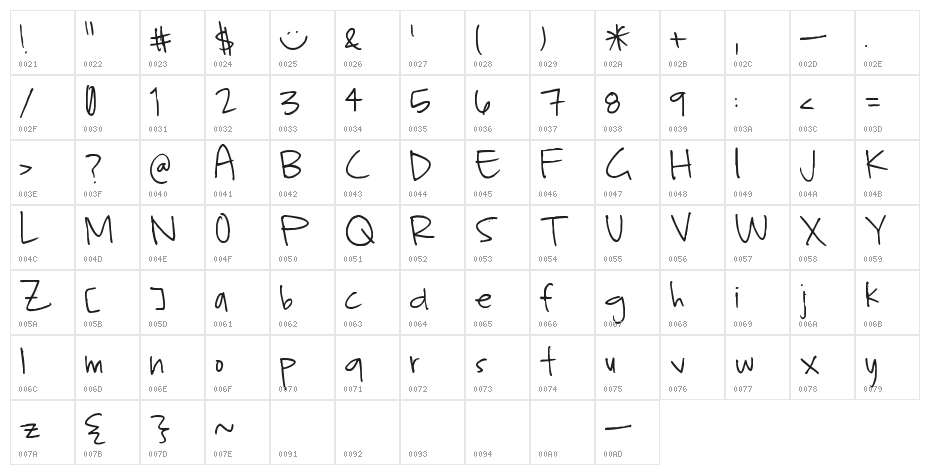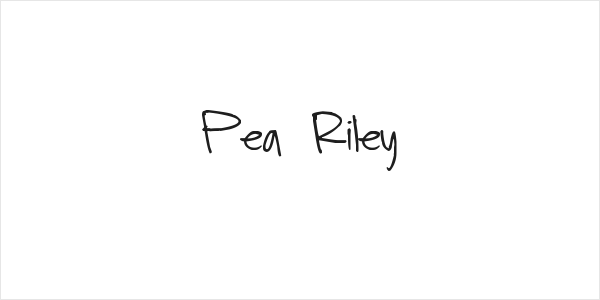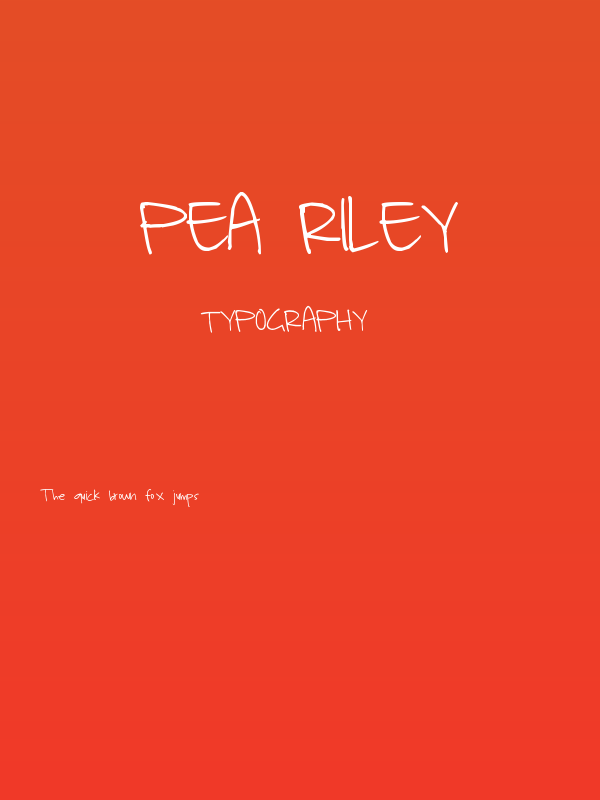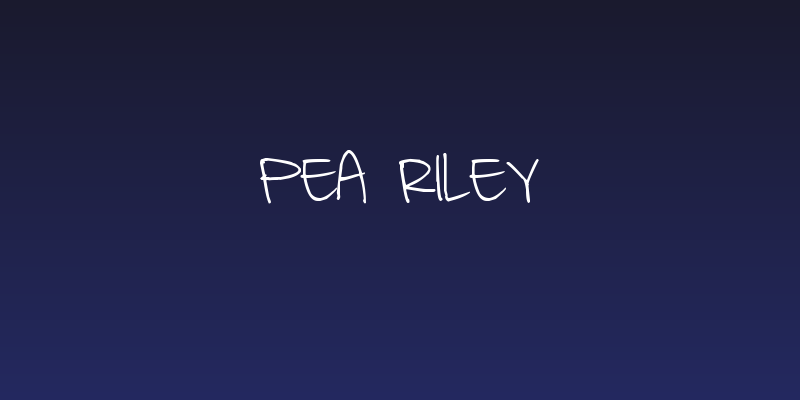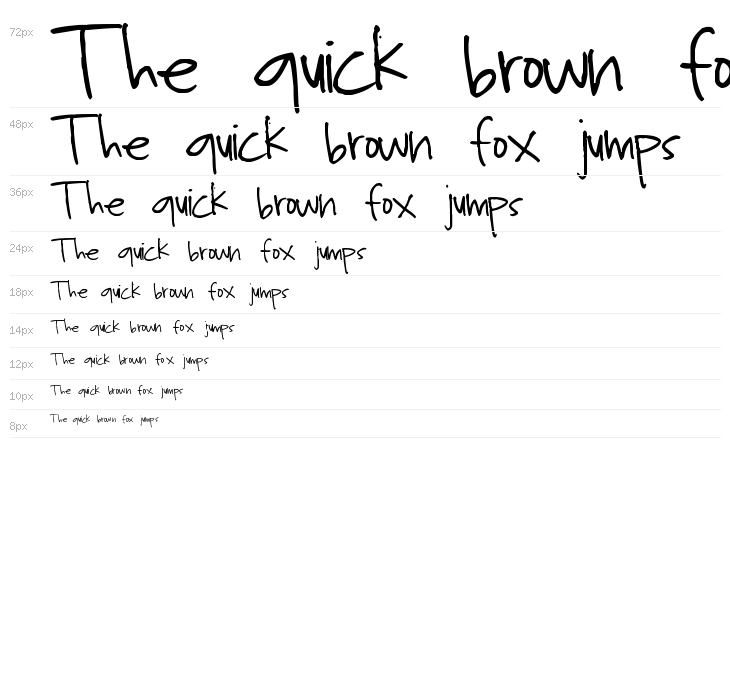
Pea Riley Font
| Gesamtstil | Casual |
| Anwendungsfall | Headlines, Informal text, Creative projects |
| Vorgeschlagene Projekte | Ideal for greeting cards, personal blogs, children's books, and creative branding. |